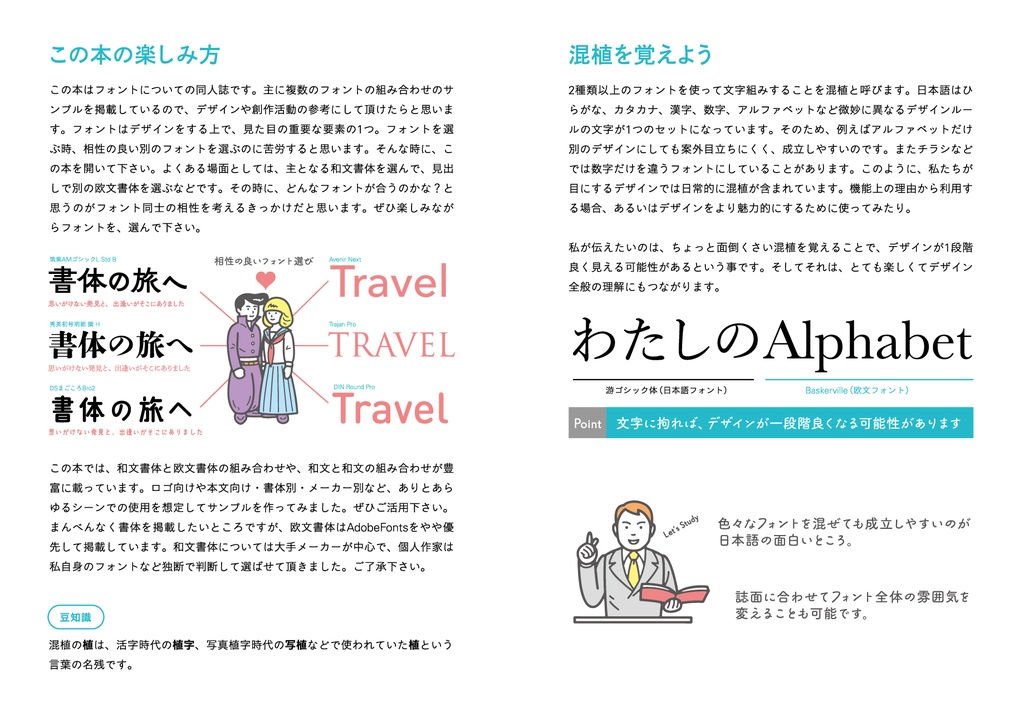
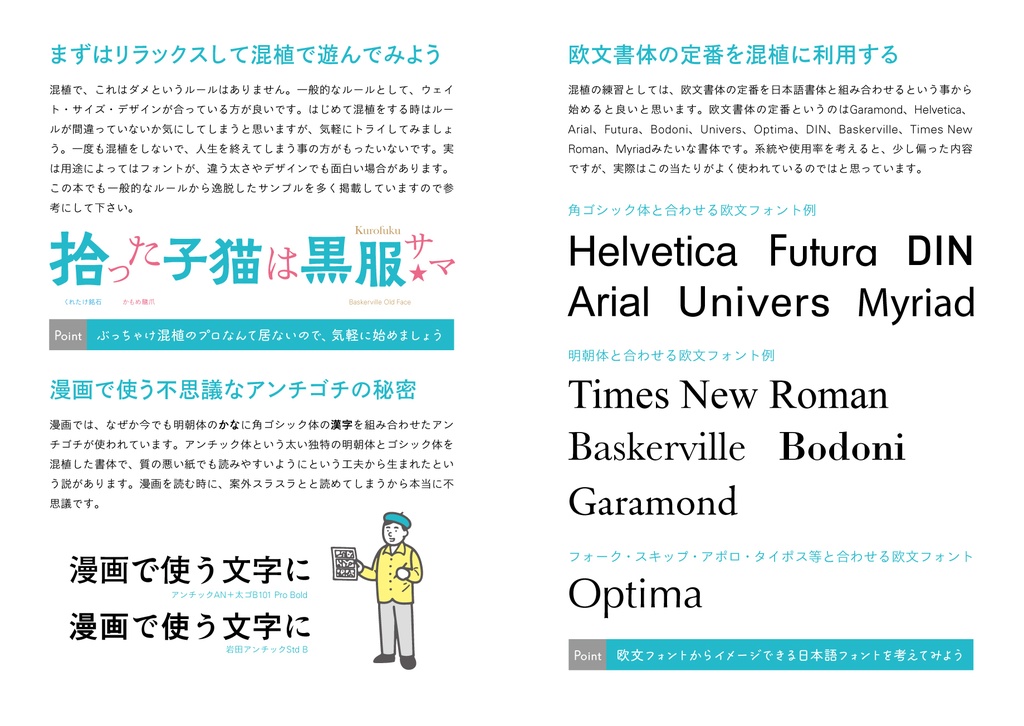
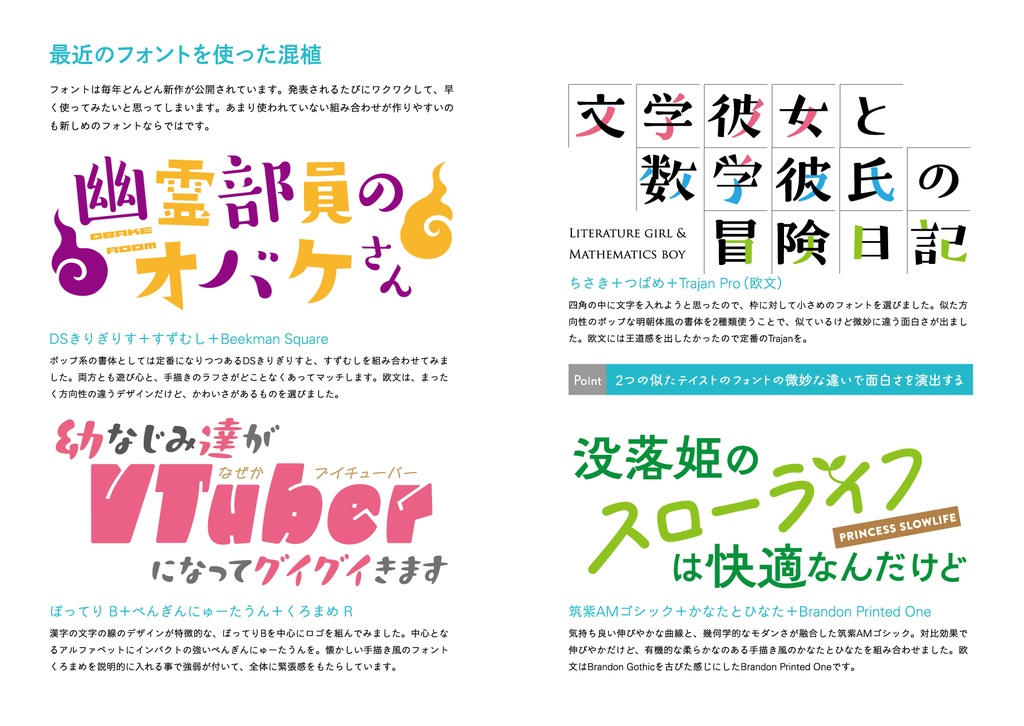
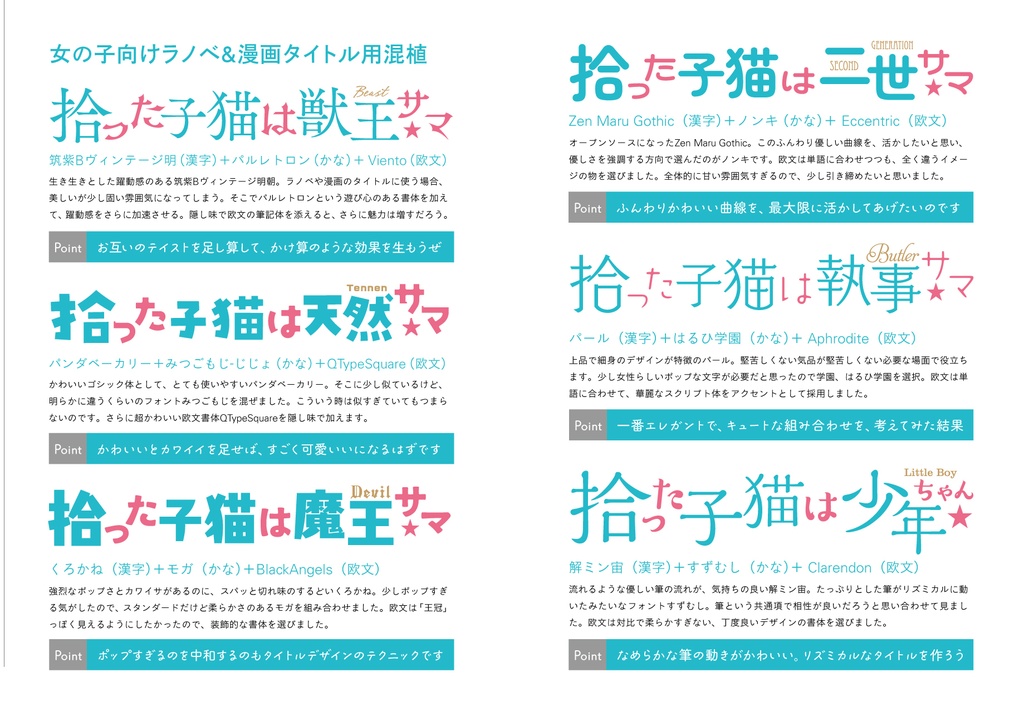
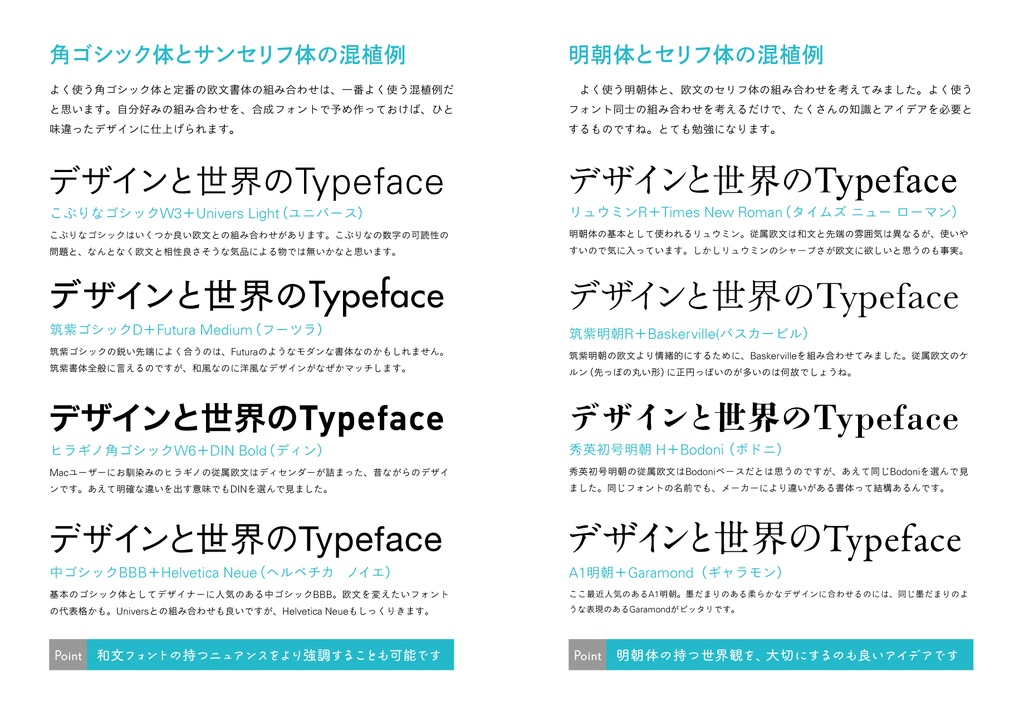
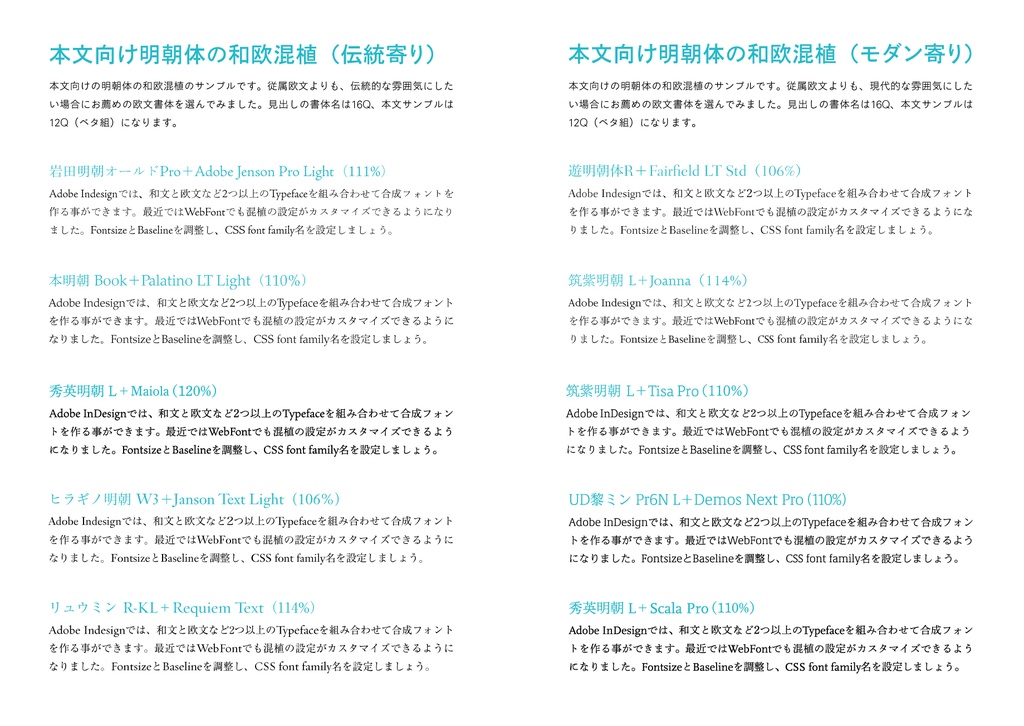
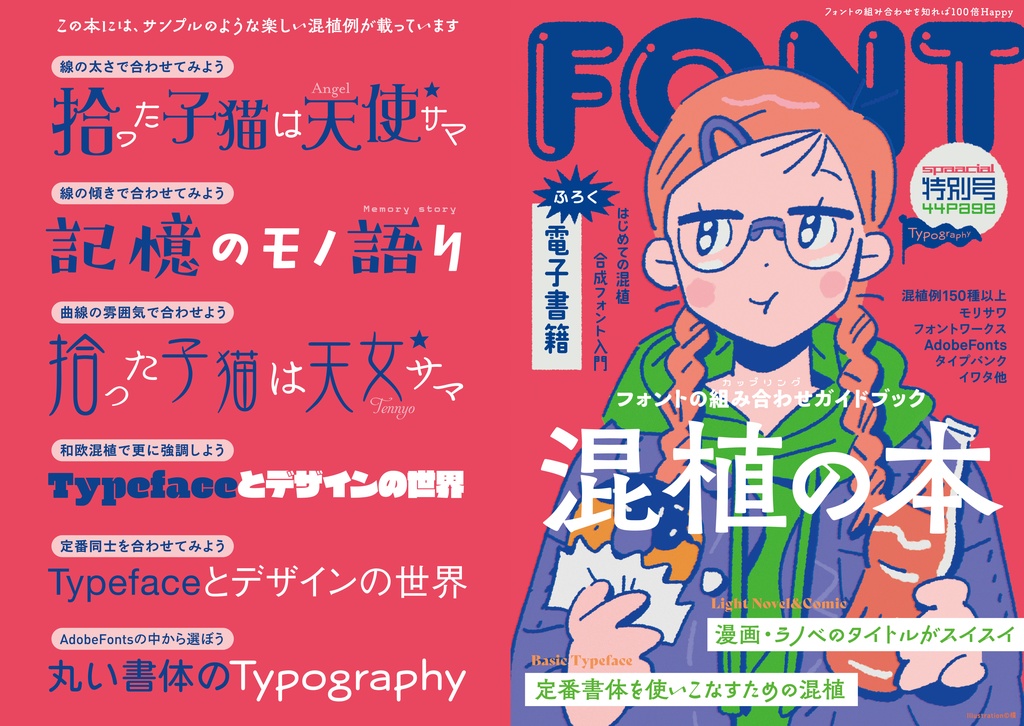
■混植の本〜フォントのカップリングガイド(同人誌版) フォントはデザインをする上で、重要な要素の1つ。フォントを選ぶ時、相性の良い複数のフォントを選ぶのに苦労すると思います。よくある場面としては、主となる和文書体に似合う欧文書体を選ぶなどです。その時に、どんなフォントが合うのかな?と思うのがフォント同士の相性を考えるきっかけだと思います。ぜひ楽しみながらフォントを、選んで下さい。 この本ではフォントの組み合わせのサンプルを200種類以上掲載してます。デザインや創作活動の参考にして頂けたらと思います。また300種類以上のおすすめフォントが覚えられるフォント見本帳としても活用いただけます。 □フルカラー全67ページ・PDF(電子書籍) ■ こんな方にオススメ! ◎入門者の方 Adobeの合成フォント機能を使ったことが無い。 同人誌のタイトルデザインのアイデアに悩む。 今持ってるフォントを、もっと有効活用させたい。 和文フォントと欧文のフォントをもっと知りたい。 ◎初〜中級者の方 一段階上のフォント選びのセンスを身につけたい。 ウェブや動画で印象的なフォントの使い方をしたい。 内容に沿った本文体のフォント選びをしたい。 ■ 読んだ後に身につくこと 代表的な和文と欧文のフォントが覚えられる。 フォントの違いが自然に身につき、適切な使い方ができるように。 【主な内容】 混植を覚えよう 和欧混植とは 混植に便利なAdobeのソフト まずはリラックスして混植で遊んでみよう 欧文書体の定番を混植に利用する 角ゴシック体とサンセリフ体の混植例 明朝体とセリフ体の混植例 男の子向けラノベ&漫画タイトルの混植 小説向けタイトルの混植例 女の子向けラノベ&漫画タイトル用混植 モリサワの和欧混植 フォントワークスの和欧混植 Adobe Fontsの和欧混植 タイプバンクの和欧混植 イワタの和欧混植 最近のフォントを使った混植 ゲームロゴ向けの混植 本文向け明朝体の和欧混植(伝統寄り) 本文向け明朝体の和欧混植(モダン寄り) DINとの和欧混植 Optimaとの和欧混植 欧文の丸ゴシック体(Rounded) 定番丸ゴシック体とAdobeFontsの和欧混植 Youtubeでのフォント使用例 似たフォント同士の混植 きれいめフェミニンな混植 筆文字と欧文の混植 かなたとひなたの混植 異国混植 混植による可愛い人名ロゴの作り方 Canva収録フォント同士の混植 この書籍で使用している混植 ■ 無料サンプル版について 15ページのサンプル版です。読んだら、ぜひ商品を買っていただけると嬉しいです。 ※この商品はPDFの「ダウンロード販売」です。紙の書籍ではありませんのでご注意ください。また内容は随時、更新および追加されます。